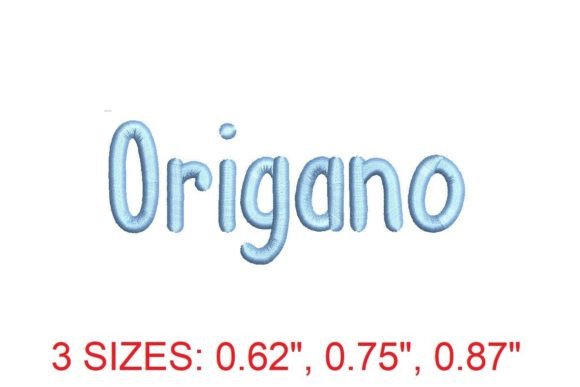
Origano Embroidery Font
Mencari elemen reka bentuk yang sesuai boleh menjadi mencabar, tetapi Origano Embroidery Font menawarkan koleksi luar biasa yang menaik taraf karya anda serta-merta.